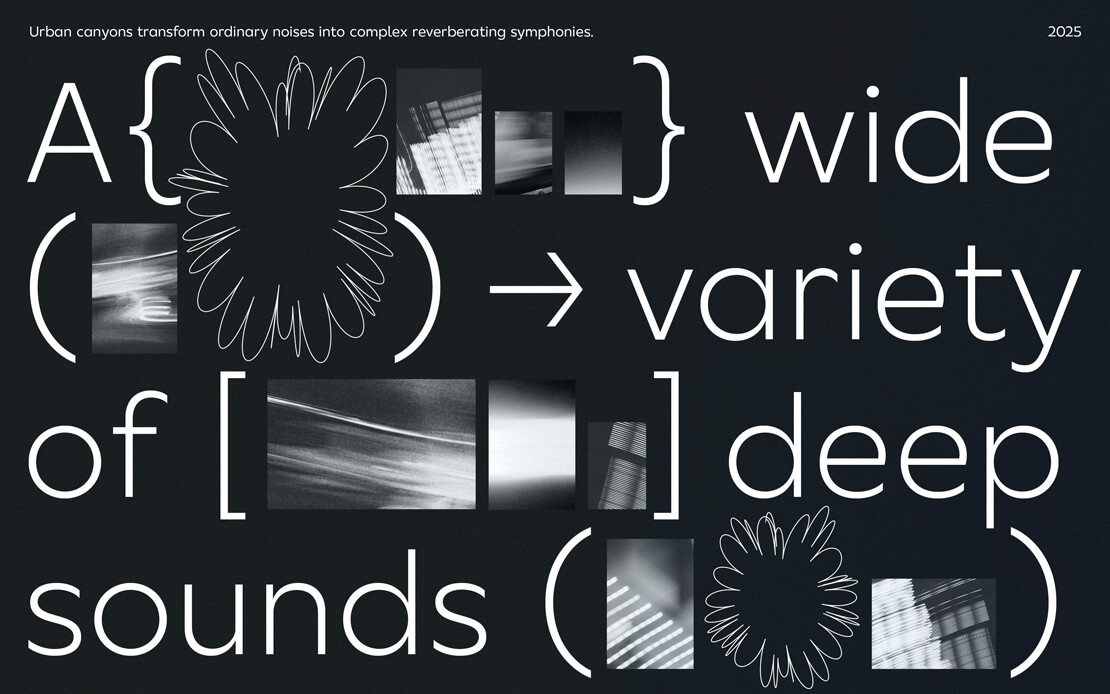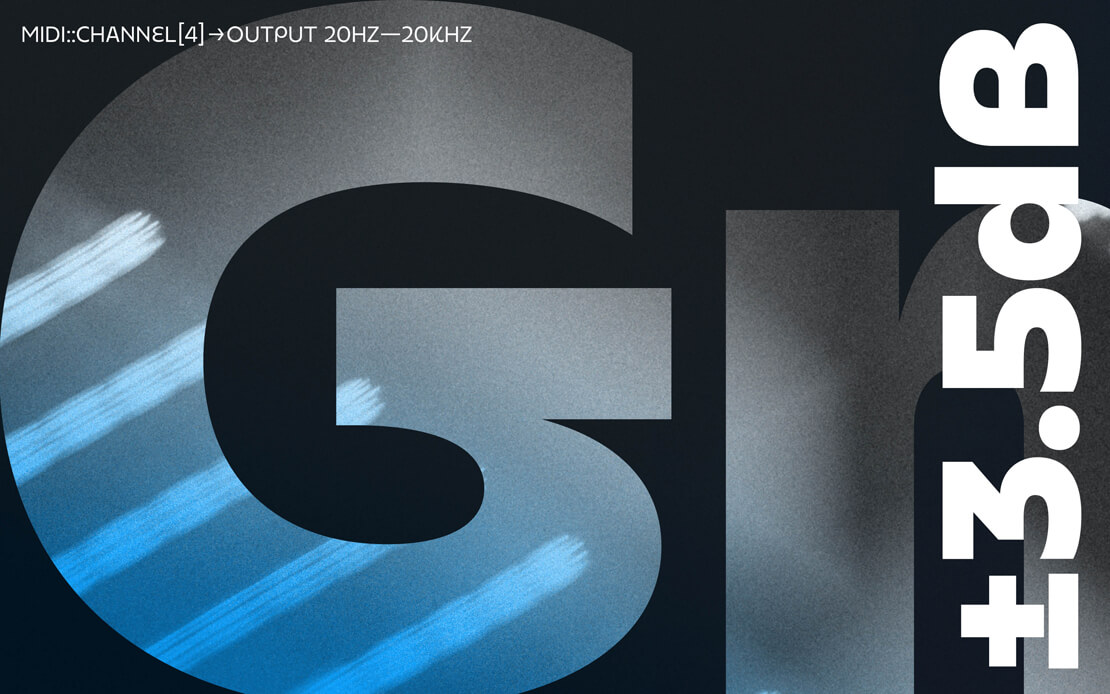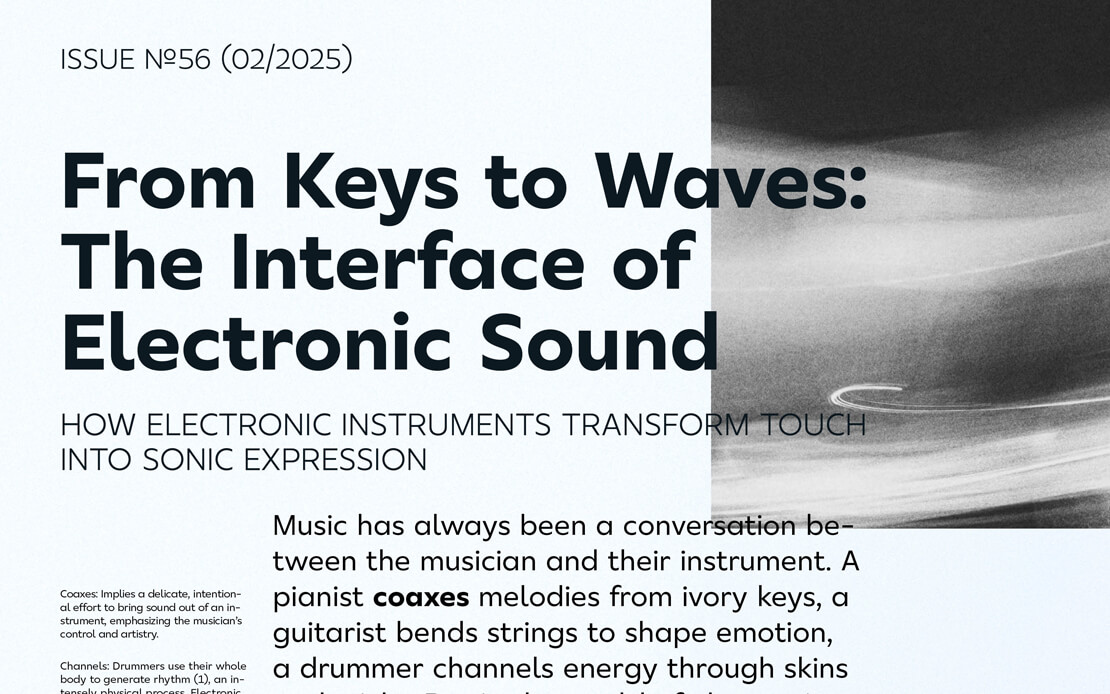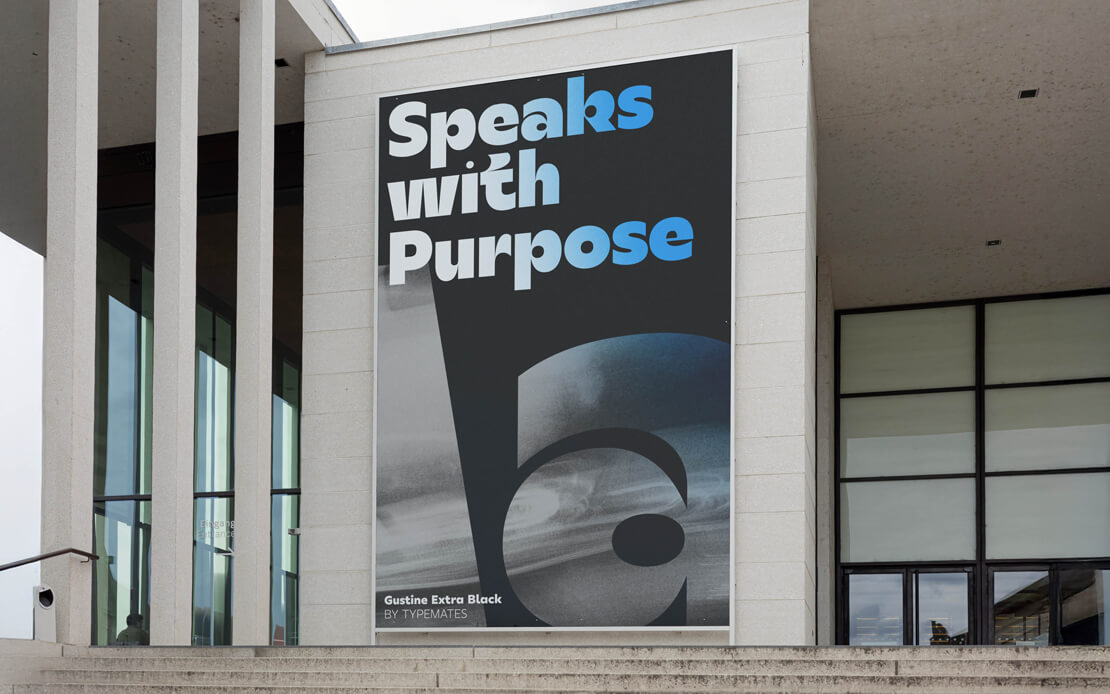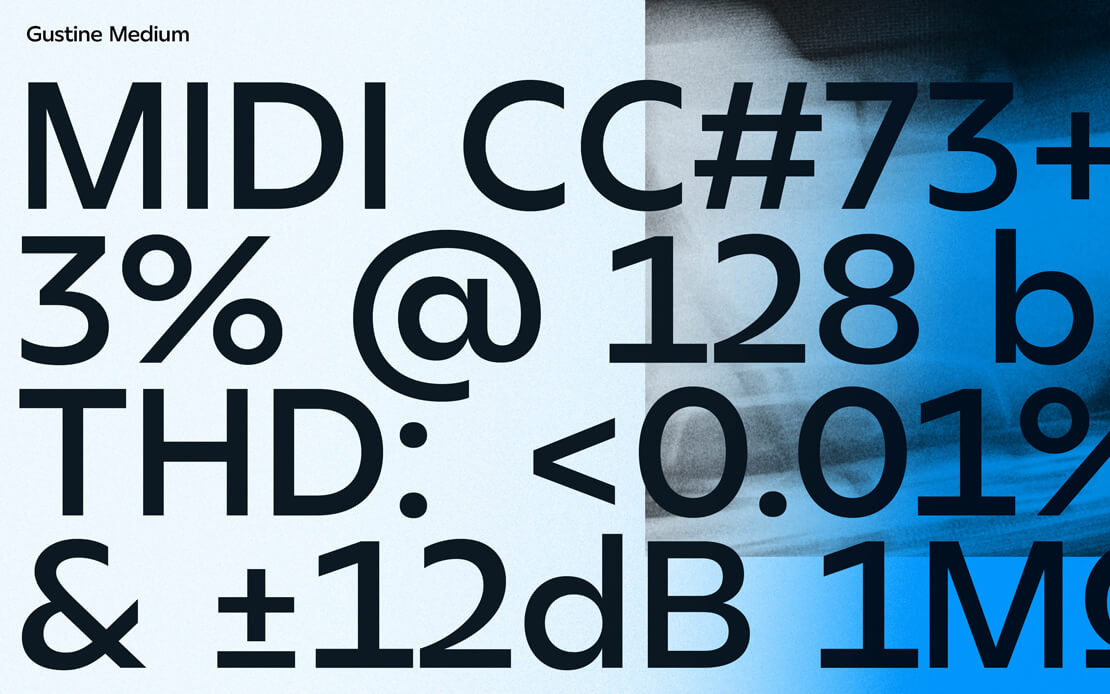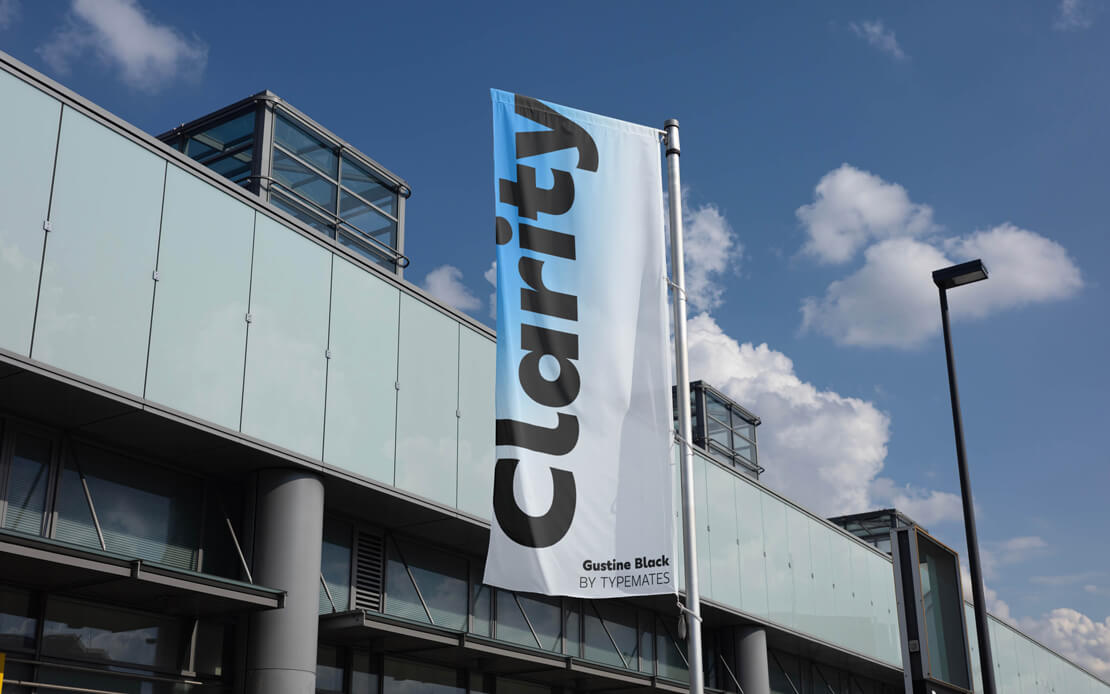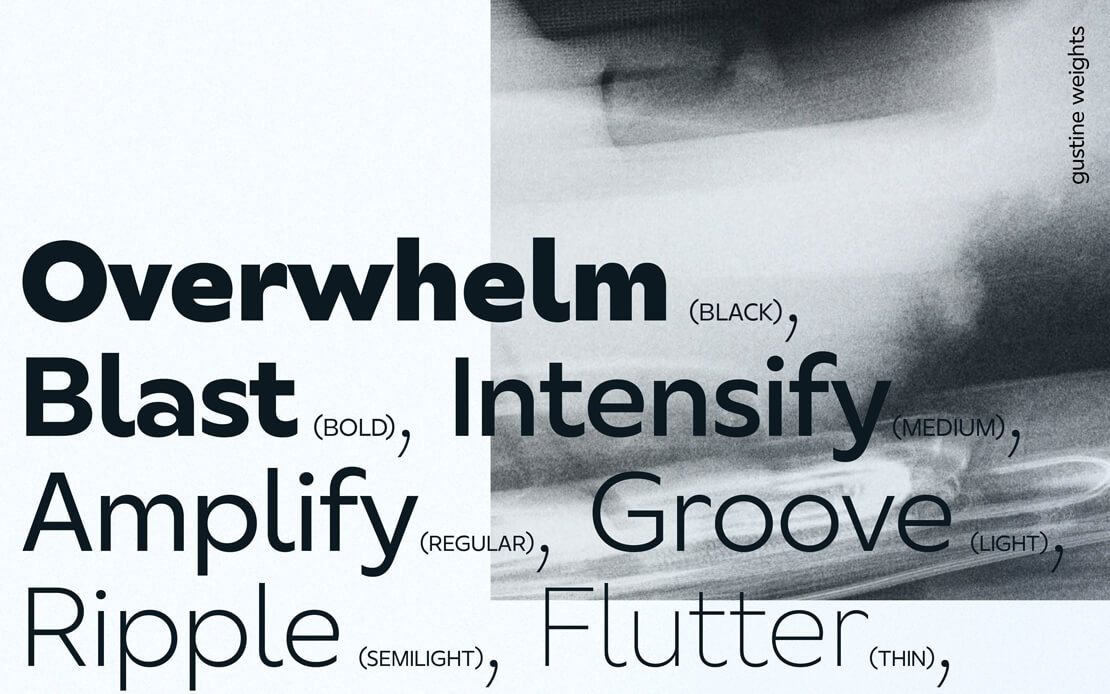
Gustine: Neue Schriftfamilie von TypeMates veröffentlicht
Mit »Gustine« stellt TypeMates ein neues Schriftsystem vor, das sich durch geometrische Klarheit und ausdrucksstarke Details auszeichnet. Entworfen von Natalie Rauch, vereint die Schrift funktionale Vielseitigkeit mit charaktervollen Akzenten.
Die Familie gliedert sich in »Gustine« für Text und Orientierungssysteme sowie »Gustine Vaganza« für markante Headlines, die durch »Gustine Extra« eine zusätzlich Ergänzung findet.
Gustine kombiniert breite Proportionen, präzise Rundungen und kantige Abschlüsse zu einer Schrift, die sich gleichermaßen für Fließtext, digitale Anwendungen und Beschilderungen eignen kann. Neben sieben Strichstärken bietet sie eine Auswahl alternativer Zeichenformen sowie einen erweiterten Zeichensatz für über 200 Sprachen.
Gustine Vaganza erweitert das Schriftsystem um kalligrafisch inspirierte Elemente mit verspielter Anmutung. Charakteristische Buchstabenformen und kreative Details verleihen dem Stil eine lebendige, fast handschriftliche Note. Die ergänzende Variante Gustine Extra überspitzt diese Eigenschaften und bietet dekorative Initialen sowie starke Kontraste für den Einsatz in aufmerksamkeitsstarken Designs.
Die Stile unterstützen eine umfangreiche Emoji-Sammlung und sind technisch auf professionelle Anwendungen ausgerichtet.